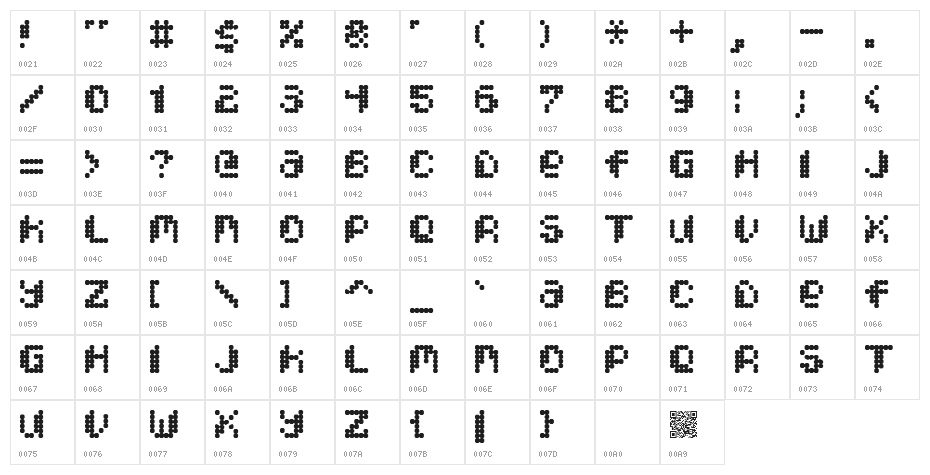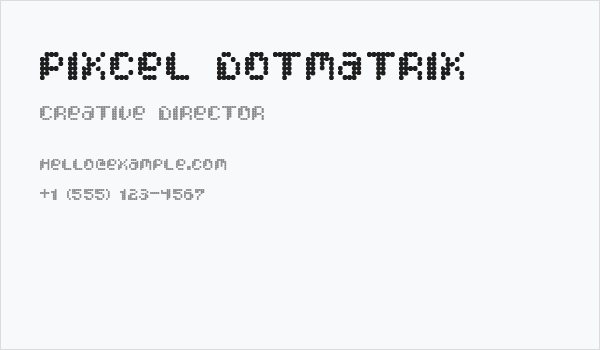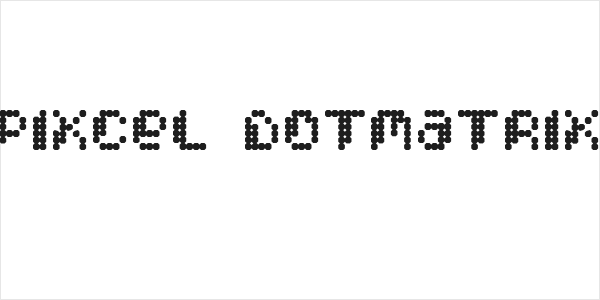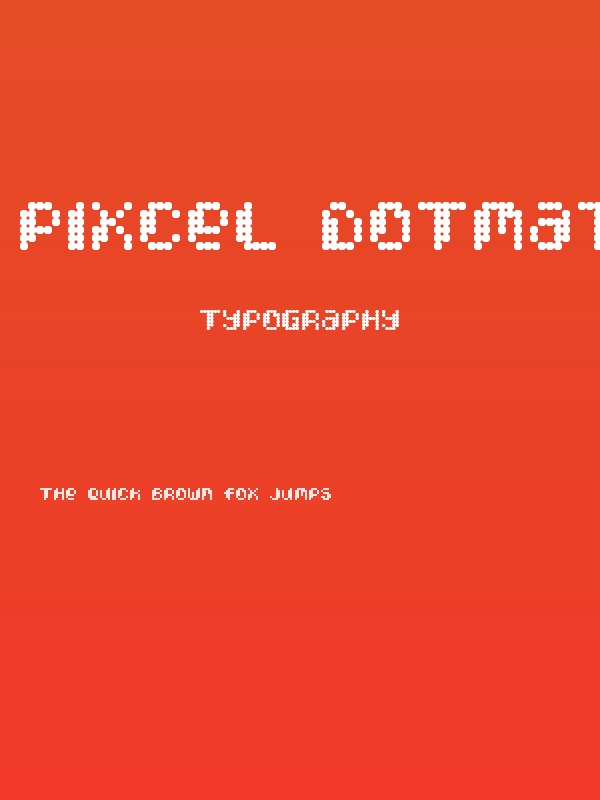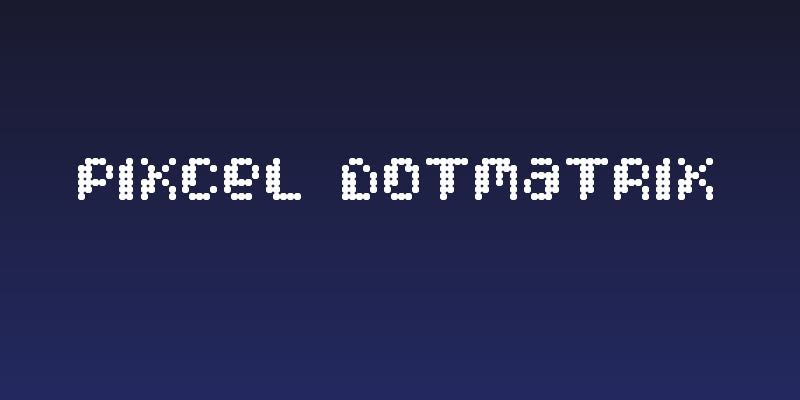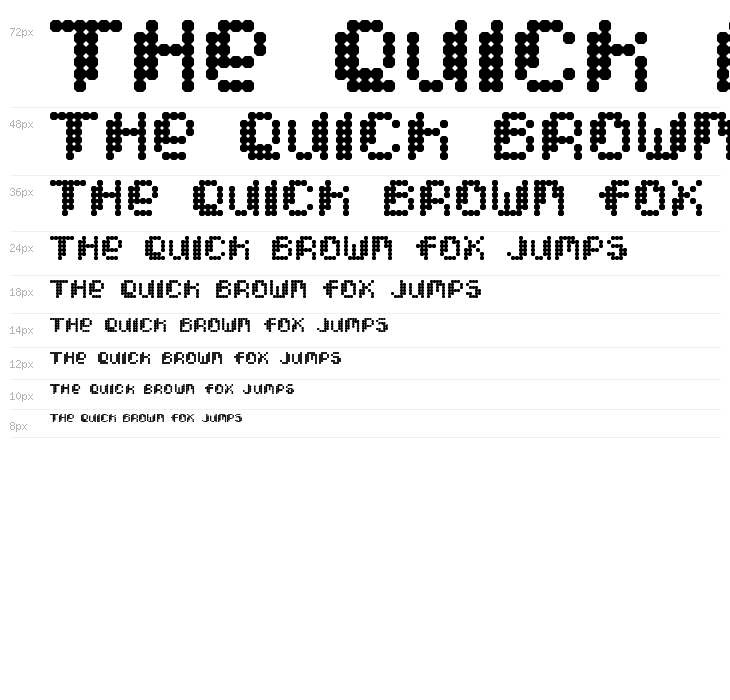
Pixcel DotMatrix Font
| Stile generale | Retro, Digital |
| Progetti proposti | Ideal for digital-themed designs, retro video game graphics, tech-related branding, and any project requiring a vintage digital look. |